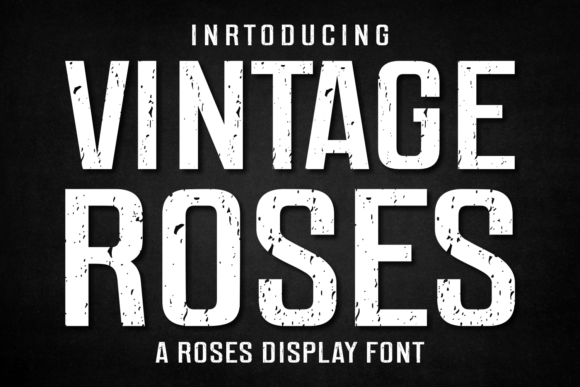
Vintage Roses
Việc tìm kiếm các thành phần thiết kế phù hợp có thể là một thách thức, nhưng Vintage Roses cung cấp một bộ sưu tập đặc biệt giúp nâng tầm công việc của bạn ngay lập tức.
Cho dù bạn đang tạo sản phẩm POD (In theo yêu cầu), thiệp mời đám cưới hay đồ họa mạng xã hội, Vintage Roses đều là một sự lựa chọn lý tưởng.